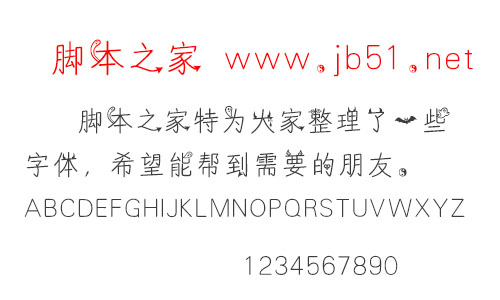
漢儀小惡魔簡字體是一款以POP字體為原型修改的卡通字體,并添加了萌萌的惡魔卡通圖案進(jìn)行裝飾,非常有趣,讓用戶通過字體去傳達(dá)另一種氣質(zhì),展現(xiàn)腹黑,愛開玩笑的個性。歡迎喜歡漢儀小惡魔簡的朋友前來下載使用。
字體筆畫特點
依照家書體的字形結(jié)構(gòu),結(jié)合小惡魔壞壞的形態(tài),筆畫較溫潤,不至于完全偏向邪惡的理念,反而是一種俏皮、愛搗蛋的形象。 字體設(shè)計理念:“小惡魔”的形象擴(kuò)展開,類似蝙蝠,叉子,小尾巴等形態(tài)與家書體重新組合。